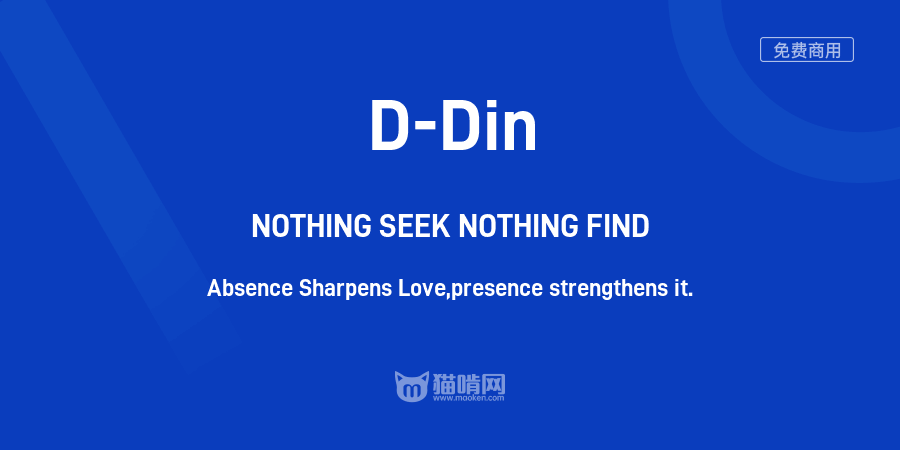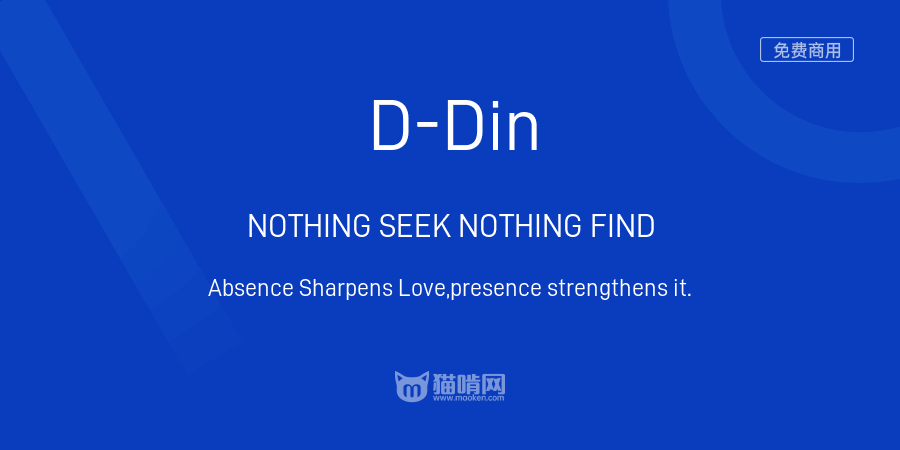
D-Din
DIN1451是一种广泛用于交通的无衬线字体,行政和技术应用。它是由德国人定义的德国标准协会标准化)在标准表DIN 1451 Schriften(字体)中1931类似的标准也适用于印刷字体。
最初设计用于工业用途,第一个DIN字体是技术难度有限的简化设计。由于设计的易读性和简单,朴素的设计,它有在标牌和显示调整中成为通用用途。许多对原设计的修改和扩展已经发布数字化。